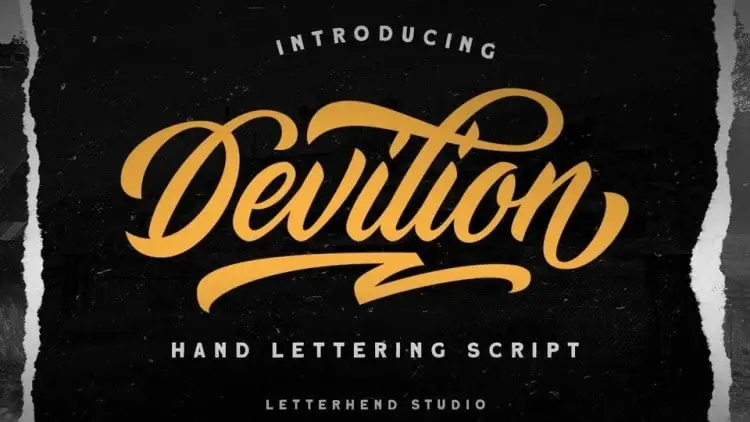
Devilion Bold Script Font – Download Grátis
Devilion Bold Script é uma fonte retro criada pela Letterhend Studio com acabamentos chamativos e alternativas interessantes. Esta fonte oferece uma sensação do estilo retro que os anos 60 e 70 estavam acostumados a gerar. É perfeitamente projetada para ser aplicada em logotipos vintage, rótulos, selos, revistas, capas de livros, embalagens, moda ou qualquer tipo de propaga. Esta fonte é o que você precisa se estiver buscando um toque nostálgico no seu trabalho gráfico de arquitetura digital e design editorial. Seja em uma aplicação simples de texto, um logotipo complexo ou até mesmo um projeto visuais incrivelmente detalhado, essa fonte vai tornar suas criações únicas e memoráveis. Descubra o poder da Devilion Bold Script para criar experiências visualmente fascinantes em seu próximo projeto.